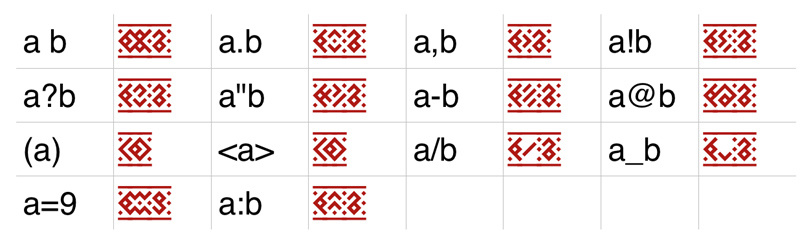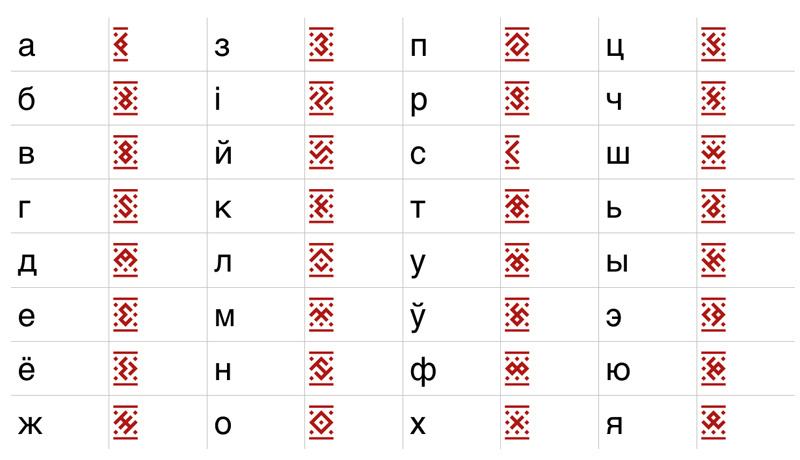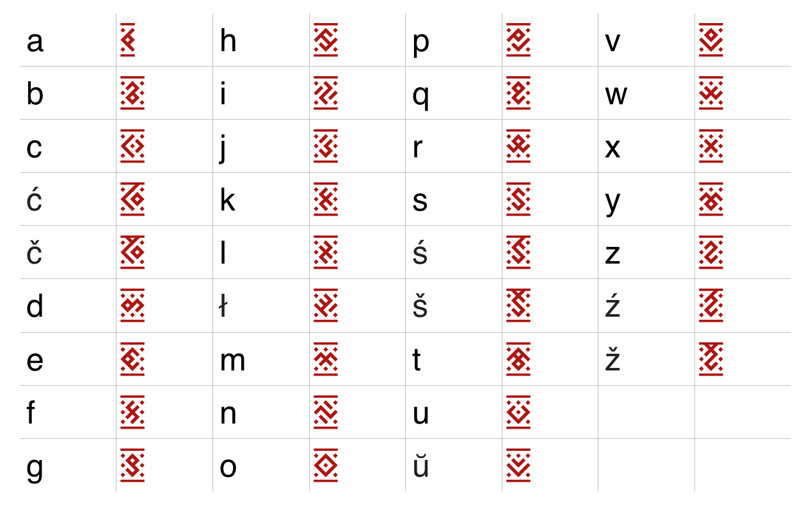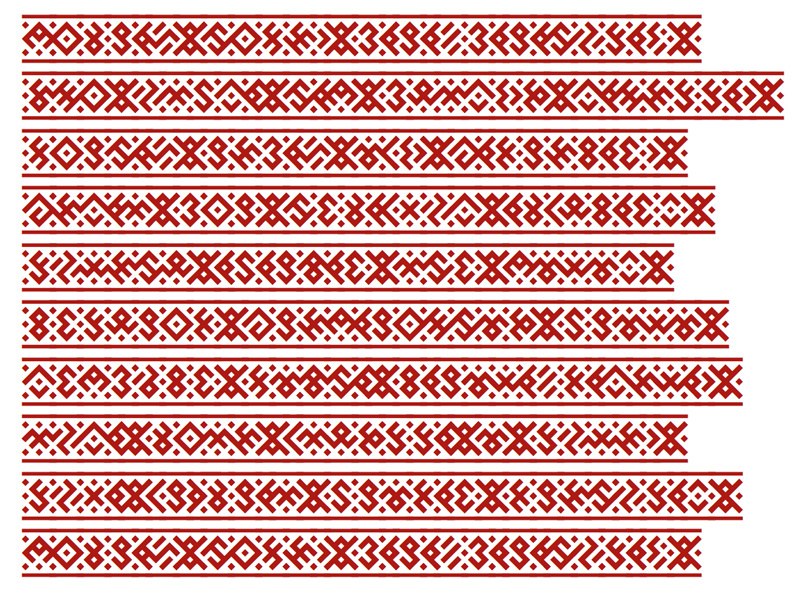
Шрифт-орнамент
Философ и санскритолог Михаил Боярин разработал новый для Беларуси стилизованный шрифт из элементов белорусского орнамента
Михаил преподавал санскрит более 10 лет. Одно время даже изучал санскрит в Индии — в санскритским университете Сампурнанд. Его увлечение шрифтами началось оттуда.
У Михаила есть мечта — создать неповторимое национальное письмо, знаковую систему.
«Она будет сберегать наш смысловой ресурс. Эту мечту я постепенно осуществляю, создавая шрифты. В сакральным смысле шрифт — это жертва богине Родины. Ведь «сакральный» на самом деле означает «жертвенный».
Шрифт «Берегиня» — декоративный и возник по наитию, работа над ним заняла несколько часов. Это стилизация кириллического и латинского алфавита узорами белорусского орнамента.
Он предназначен для оформления заголовков, вывесок магазинов, визуальной рекламы, журналов, сайтов.
Как говорит сам Михаил Боярин: «Поэты могли бы печатать такими шрифтами свои стихи с параллельным текстом, поскольку это тот случай, когда вид текста имеет значение. Я хотел бы, чтобы в Беларуси появился четкий узнаваемый национальный стиль».
Вообще, для философа «Берегиня» — это часть более крупного проекта «Свамова. «Это идеал чистого и в смысле словообразования свободного белорусского языка», — объясняет суть проекта Михаил.
Письмо Свамовы будет основана на национальной матрице знаков, присутствующих в узорах белорусского орнамента. Оно будет состоять из двух частей.
Первая — это морфологическое письмо, знаки которого образуют смысл корней и аффиксов.
Такое письмо должно выражать не внешнюю сторону языка, его звучание, а его глубокую сущность и строение.
Второй частью будет фонематическое письмо — для имен собственных и слов, которые необходимо передать фонетически.
Кроме «Берегини», еще один шрифт — «Стрела» — наследует несколько иной орнаментальный стиль. Здесь сочетаются и белые, и красные узоры.
Поэтому чтобы читать такой шрифт, нужна специальная концентрация.
Но в перспективе автор идеи собирается разработать более читаемый и скорописный вариант шрифта, который можно будет быстро писать от руки.
Автор обещает даже создать флэш-анимация с уроками письма.
Как говорит Михаил: «Читаемость — дело привычки. Чтобы читать то письмо, которым мы теперь пользуемся постоянно, мы потратили в детстве несколько лет».
Поэтому таинственность шрифта, по мнению Боярина, пойдет только на пользу: «Совершенно прозрачный шрифт был бы неинтересен, но я попробую поработать над его читаемостью. Разработчики декоративных шрифтов часто гонятся за читаемостью. Когда же мы вводим новое письмо или стиль — сразу достичь читаемости не получится».
К тому же Михаил считает, что новые шрифты — отличная игра для белорусских парней и девушек.
Философ Гедар Джемаль, «которого я очень уважаю», сказал замечательную фразу: «Никогда не подняться тому, кто инвестировал свой смысловой ресурс в чужую знаковую систему», замечает Михаил Боярин.